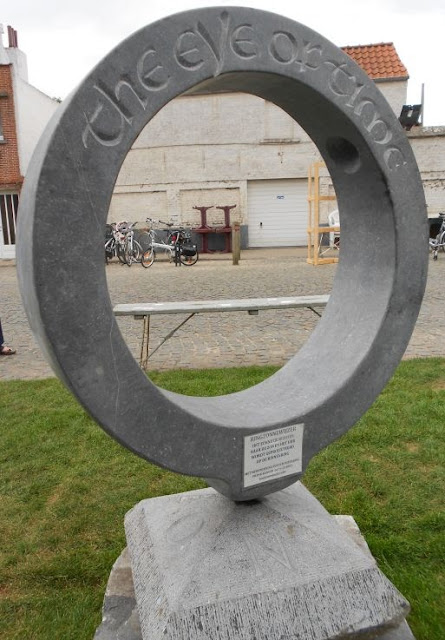
BEELDENROUTE IN LISSEWEGE
ROTA DE ESCULTURA EM LISSEWEGE
In Lissewege loopt voor de 19de keer de
Beeldenroute, nog tot 15 september. Ik vond er ook deze mooie letters in steen
van Frank Ranson.
Em
Lissewege, até dia 15 de setembro, continua a 19a edição da Rota de Escultura. Aí encontrei
também estas belas letras em pedra de Frank Ranson.
| IL EST TOUJOURS L'HEURE DE NE RIEN FAIRE |
| EARTH-AIR-FIRE-WATER |
| TËTE À TËTE |
| THE EYE OF THE WIND |
In het dorp vind je ook deze.
Na aldeia também encontram-se estas.
| WIJNHANDEL - COMÉRCIO DE VINHO |
| BED AND BREAKFAST |
| ONDE NÓS ANDAMOS - ALGUMA VEZ VÃO CRESCER ROSAS |
| BEELDENROUTE - ROTA DE ESCULTURA |